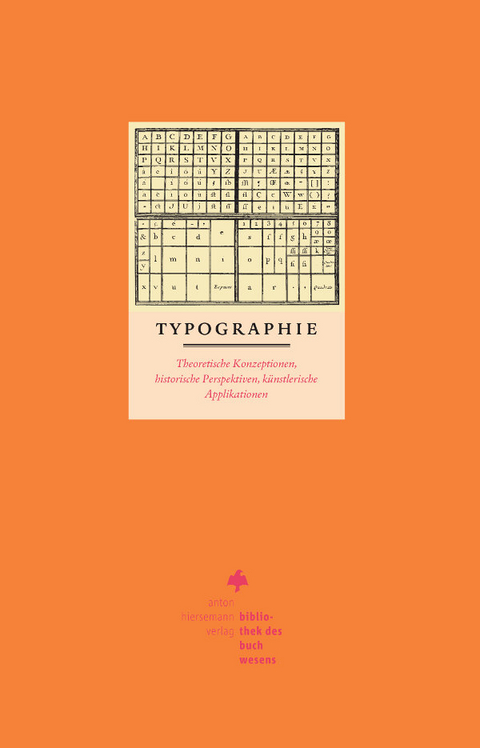
Typographie
Theoretische Konzeptionen, historische Perspektiven, künstlerische Applikationen
Typographie als jede Form gestalteter Schrift ist ein wichtiges Mittel der Schriftkommunikation. Sie ist geprägt von vielfältigen, sich wandelnden soziokulturellen Bedingungen, ihr Verständnis damit Aufgabe vieler Disziplinen.Der ansprechend gestaltete Band versammelt 21 illustrierte Überblicksartikel und damit verbundene Fallstudien zu zentralen typographischen Themen, verfasst von ausgewiesenen FachwissenschaftlerInnen. Alle Beiträge sind inhaltlich eng miteinander vernetzt, ihre Zugänge reichen von der Semiotik und Schriftlinguistik bis zur Literatur-, Übersetzungs- und Editionswissenschaft und weiter zur Buchwissenschaft und Kunstgeschichte.
Ursula Rautenberg ist Professorin i. R. für Buchwissenschaft an der Friedrich-Alexander-Universität Erlangen-Nürnberg.
Anja Voeste ist Professorin für Historische Sprachwissenschaft und Sprachgeschichte des Deutschen an der Justus-Liebig-Universität Gießen.